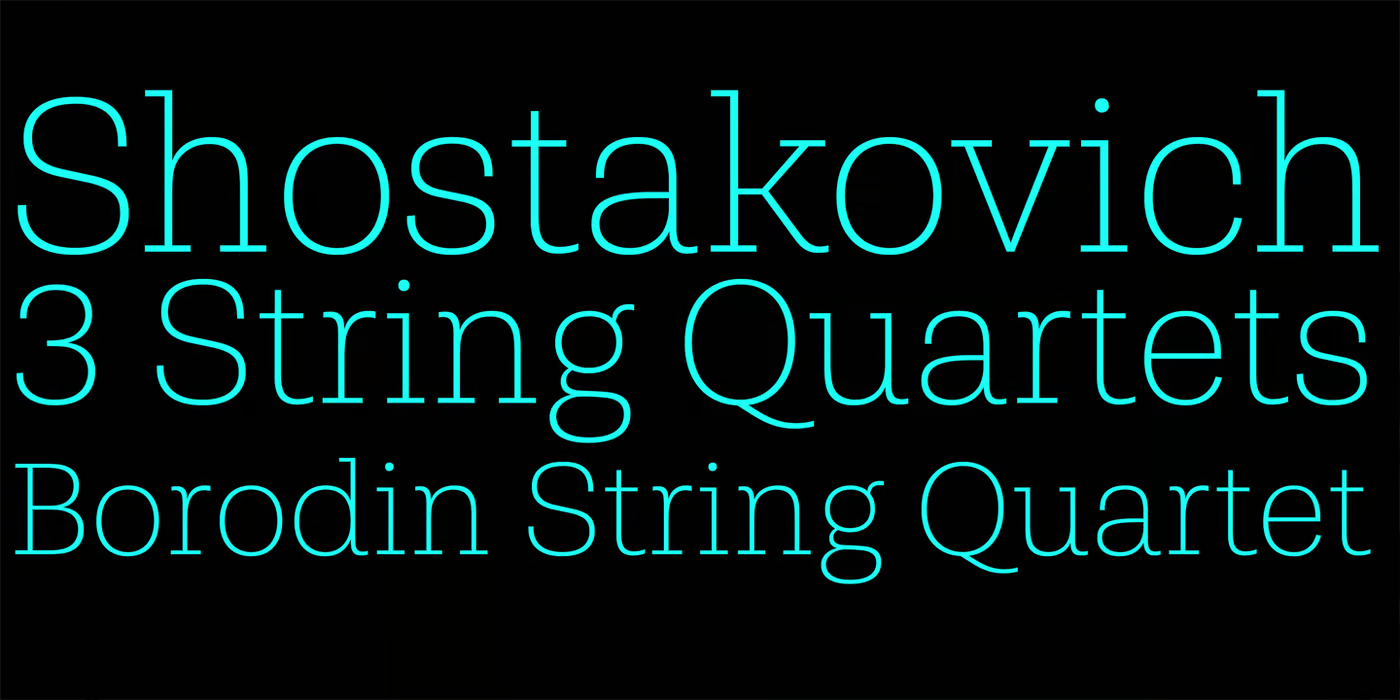
Shandon Slab Font Family
Description de Shandon Slab Font Family
Shandon Slab est une nouvelle police qui offre une nouvelle approche de la famille de polices populaire avec la prédominance des empattements. Sa particularité est que ses caractéristiques se caractérisent par une transition douce, ce qui est assez différent des autres polices de la catégorie. L’utilisation de deux styles italiques différents donne une touche vivante au design. Affichage de manuels scolaires, en particulier pour les éditoriaux, les titres et toute autre application nécessaire pour attirer l’attention des gens, Shandon Slab est idéal. La famille de polices comprend 18 styles et est présentée en OpenType avec la prise en charge de plus de 40 langues. Des ligatures standard et discrétionnaires, des chiffres de doublure proportionnels, des chiffres de doublure tabulaires, des chiffres proportionnels à l’ancienne, des chiffres de doublure à l’ancienne, des symboles monétaires correspondants, des chiffres de fraction et scientifiques, des flèches correspondantes et des caractères alternatifs sont fournis dans chaque poids.